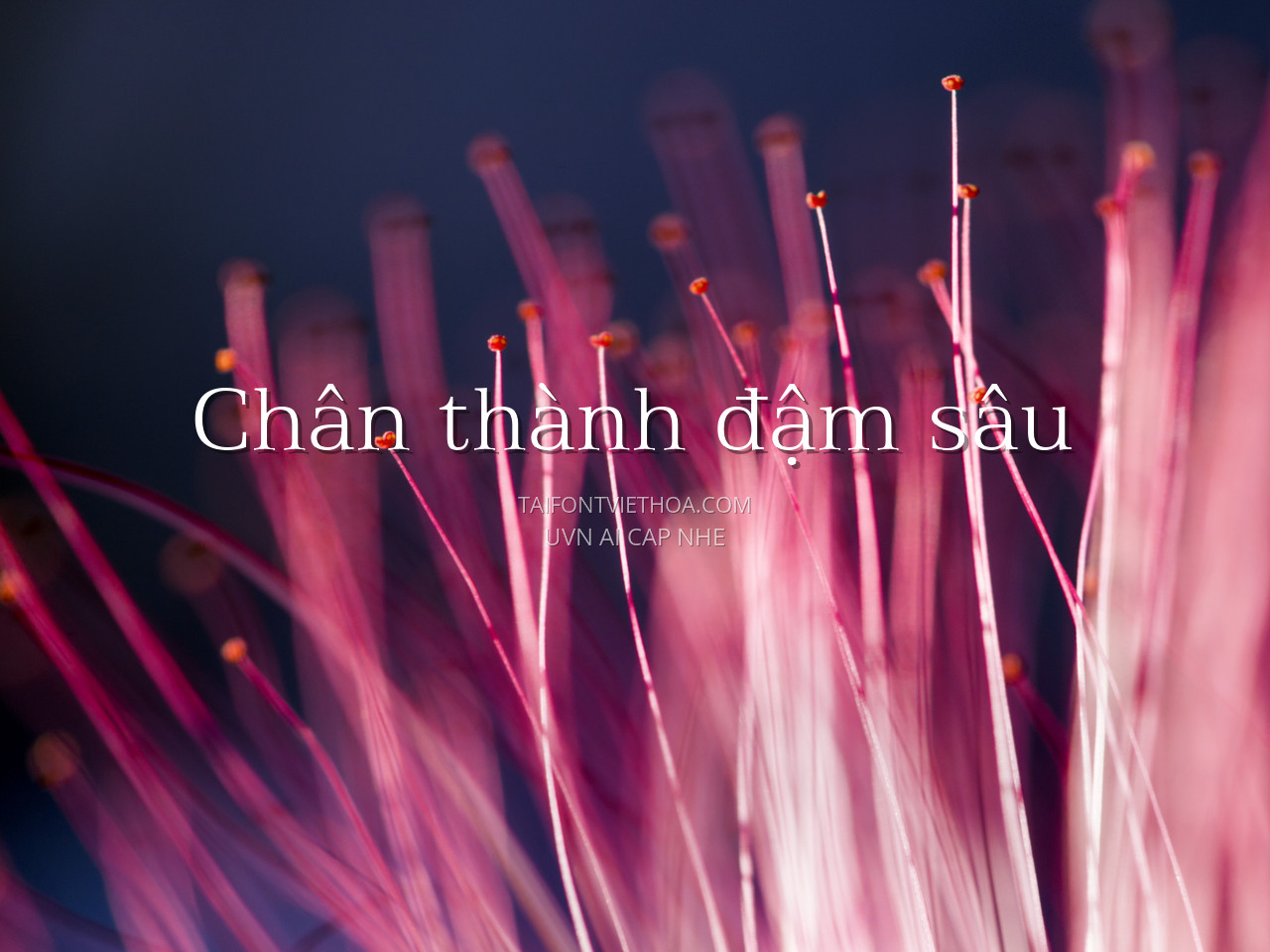
Font việt hóa UVN Ai Cap Nhe
Giới thiệu về font UVN Ai Cap Nhe
UVN Ai Cap Nhe là phiên bản nhẹ của bộ font Ai Cập cổ điển UVN, mang phong cách slab serif cổ điển pha chút hơi hướng retro. Với nét mảnh, nhẹ nhàng nhưng vẫn giữ được cấu trúc vững chắc của slab serif, font này thích hợp cho các thiết kế cần truyền tải thông điệp cổ điển nhưng thanh thoát. Font được sưu tầm và chia sẻ bởi thành viên của Font Chuẩn và đã được taifontviethoa.com chọn lọc, thử nghiệm kỹ lưỡng để đưa vào ứng dụng trong các dự án văn hóa, giáo dục và truyền thông mang màu sắc lịch sử.
Đặc điểm thiết kế và ứng dụng của UVN Ai Cap Nhe
Với các chân chữ vuông, bố cục gọn gàng và nét chữ mảnh vừa phải, UVN Ai Cap Nhe tạo nên cảm giác nhẹ nhàng, cổ kính nhưng không quá nặng nề. Font giữ được sự đặc trưng của phong cách Ai Cập cổ, đồng thời phù hợp cho trình bày văn bản dài hoặc tiêu đề trang nhã.
Font rất phù hợp cho các thiết kế như bìa sách cổ, tạp chí văn hóa, tài liệu giáo dục, thiệp mời mang hơi hướng truyền thống, thiết kế bảo tàng, hoặc các ấn phẩm liên quan đến lịch sử và di sản. Ngành nghề ứng dụng gồm: giáo dục, xuất bản, văn hóa – nghệ thuật, truyền thông cổ điển, bảo tàng và quảng bá di sản.